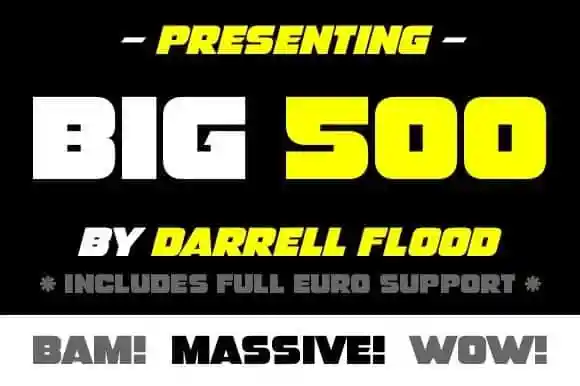
A Big 500 Display Font é uma escolha ideal para aqueles que buscam a resiliência visual e a riqueza estilística de um tipo de capa. Seu formato retangular, repleto de robustez e de uma forma única, é perfeito não apenas para jogos, animações e embalagens de produtos infantis, mas também para cartazes esportivos, seminários musicais e headlines em jornais. Essa fonte apresenta um design que transmite confiança e modernidade, fazendo-a uma opção versátil para qualquer aplicação visual onde a relevância e o impacto desejados são fundamentais. Com sua disposição de letras clara e definida, é perfeito para destacar seus projetos em designs gráficos profissionais e criativos sem se tornar excessivamente ocupante ou estridente. Escolha a Big 500 Display Font para dar vida à qualquer projeto visual que deseje transmitir uma imagem de força e simplicidade ao mesmo tempo.